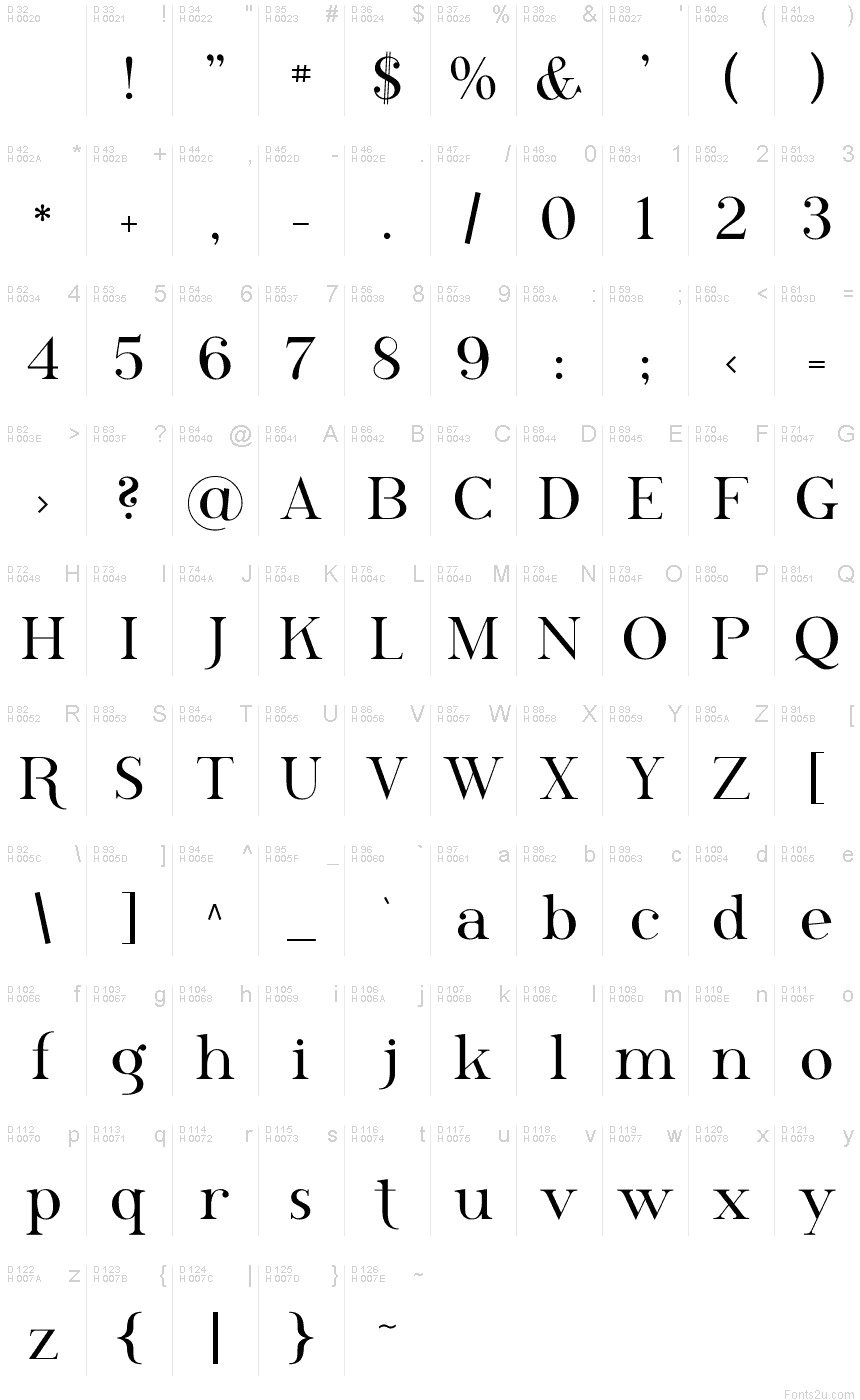
Phosphorus Selenide von Derek Vogelpohl ist eine kostenlose, kontrastreiche Serifenschrift mit einer deutlich literarischen, klassischen Anmutung. Die Buchstaben verbinden hohe, elegante Rundungen mit scharfen, keilartigen Details und dramatischen Strichstärkenkontrasten, wodurch die Schrift zwar edel wirkt, aber dennoch eigenwillig statt steif bleibt.
Damit eignet sich diese kostenlose Schrift natürlich perfekt für Buchcover, Zeitschriften-Mastheads, Plakatüberschriften, Branding für Kunstereignisse und elegante Verpackungen, bei denen ein Hauch von historischem Flair gefragt ist. Sie passt auch hervorragend zu kurzen Schlagzeilen und monogrammartigen Initialen, da die langen vertikalen Linien und abgerundeten Formen selbst wenigen Buchstaben eine komponierte und atmosphärische Wirkung verleihen.